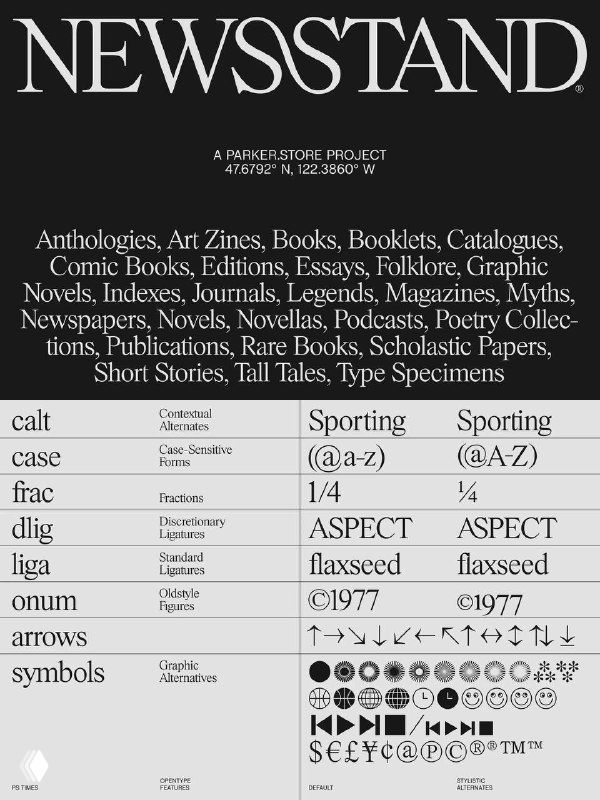
PS Times — современное переосмысление Times New Roman
Современное творческое переосмысление шрифта Times New Roman. Новой версии добавили ряд лигатур, стилистические наборы и переработали засечки.
Разработан студией Parker для использования в качестве их фирменного шрифта.
Превью семейства PS Times: тёмный постер с заголовком NEWSSTAND и образцами лигатур, засечек и таблицей символов шрифта в контексте типографики.
Образцы шрифта PS Times и таблица символов